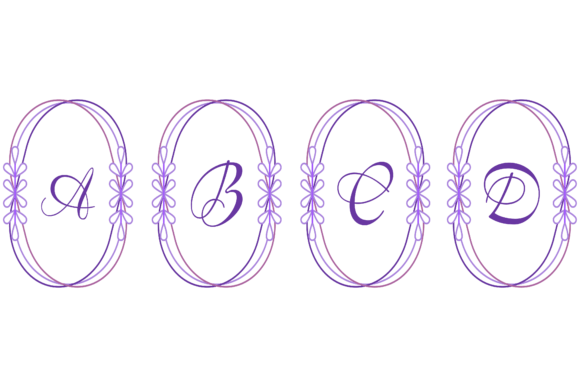
Monogram Design Font Bundle
適切なデザイン要素を見つけるのは難しい場合がありますが、Monogram Design Font Bundleは作品を即座に引き立てる優れたコレクションを提供します。
POD(オンデマンド印刷)製品、結婚式の招待状、またはソーシャルメディアのグラフィックを作成している場合でも、Monogram Design Font Bundleは理想的です。